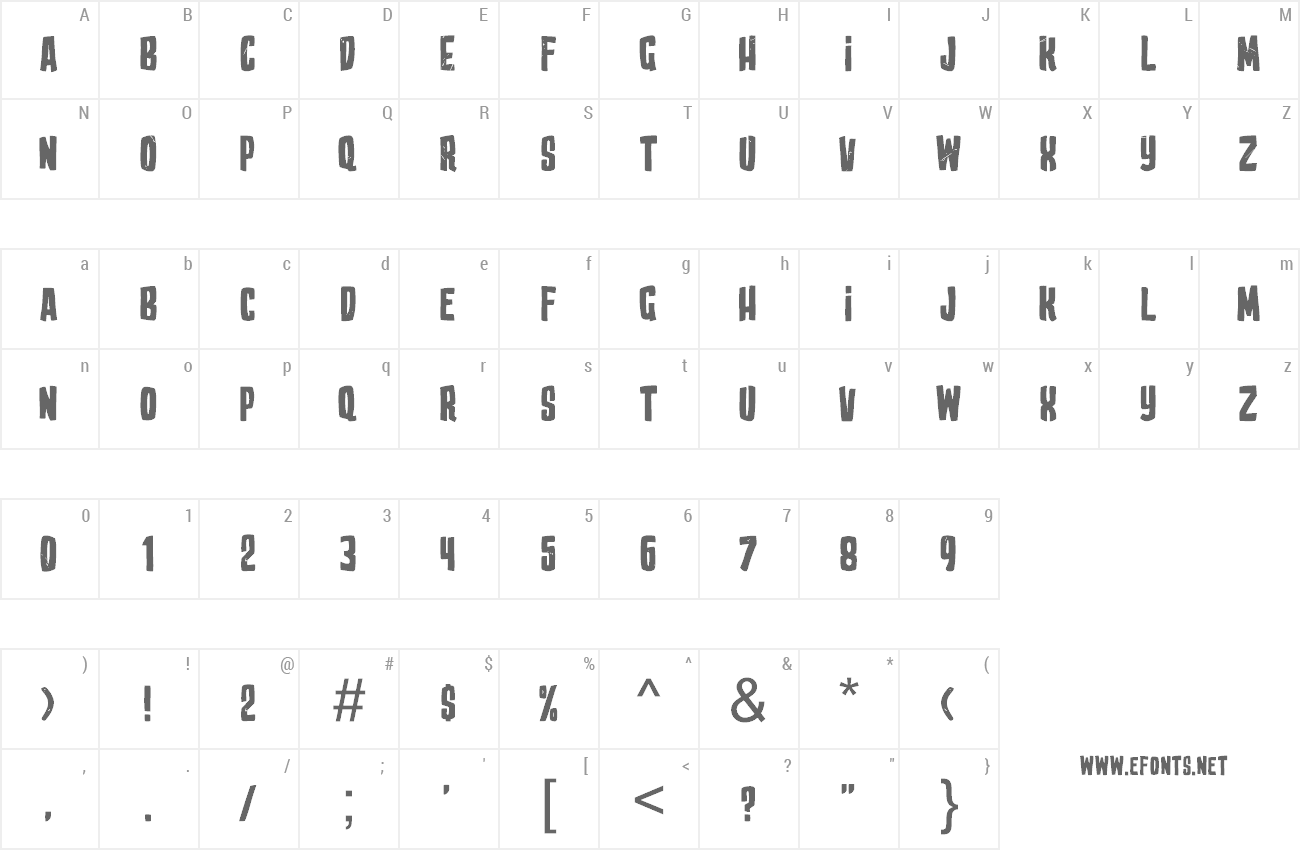
| Font name: | Ed Wood TFD |
| Author: | Tfd |
| Note by Tfd | |
Police d'�criture Ed Wood Movies, mais avec l'impl�mentation de la majorit� des caract�res sp�ciaux fran�ais et de ponctuation manquants. Note: la taille et l'espacement d'origine des caract�res sont diff�rents de l'original, un remplacement de police vers celle-ci causera des changements de mise en page. |